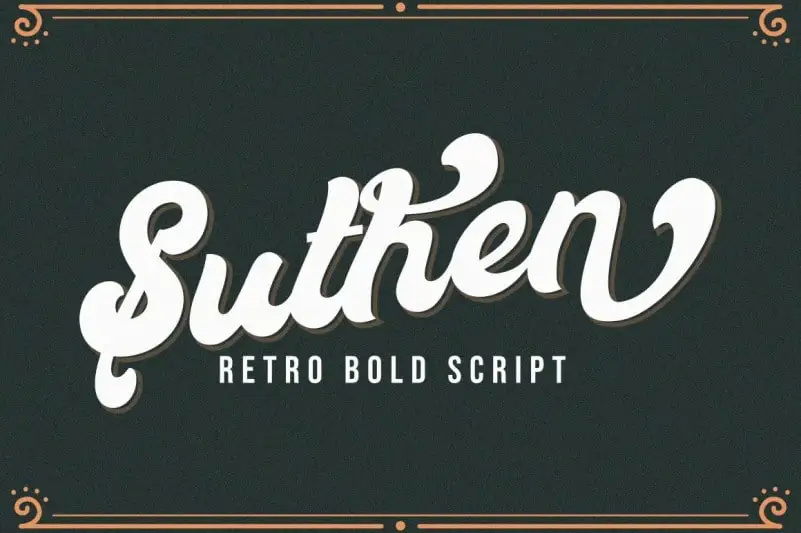
Aqui está a descrição solicitada para a página de download da font ‘Suthen Bold Script Font’: Introduzimos Suthen Bold Script Font, uma tipografia bold do tipo script que transmite um toque nostálgico. Desenvolvida pelo designer Vultype Co., esta fonte possui elementos que remetem às décadas passadas e sua estética de swashes a torna única. Perfeita para projetos com temáticas vintage ou retro, Suthen Bold Script é uma escolha ideal para criar letra vintage. Com seus detalhes curvilíneos e estilo retrô, esta fonte será um brilho em qualquer projeto que busque transmitir nostalgia e sofisticação ao mesmo tempo. Ideal para o design de logomarcas, selos ou adesivos, Suthen Bold Script é a solução perfeita para quem busca uma tipografia moderna com aparência clássica, ajudando a transformar qualquer projeto em algo único e memorável.